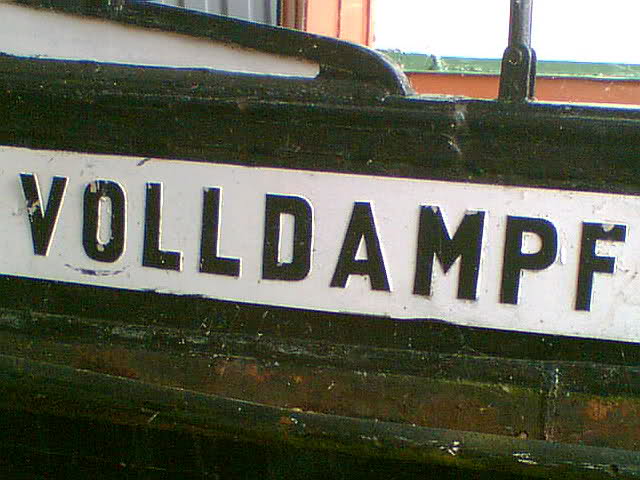
Namensschild historisches Dampfschiff
ich suche die schriftart dieses namensschildes aus stahl.
es handelt sich um das namenschild des schleppers "volldampf", baujahr 1896, des deutschen technikmuseums , siehe auch :
ich habe diese schriftart auch schon an anderen alten schiffen gesehen. ich glaube diese hier am dampfschiff "nordstern" müsste die gleiche sein, oder?
Wenn ich das richtig sehe sind das zwei verschiedene Schriften (das O sieht unterschiedlich aus). Ich glaube nicht wirklich dass es genau diese als Font gibt …
danke erstmal für die schnelle antwort! du hast wahrscheinlich recht damit, daß es sich um zwei unterschiedliche schriften handelt. bei näherem hinsehen (habe kein sehr geschultes auge..) fiel es mir auch auf.
markant finde ich die etwas gedrungene, schmale form der buchstaben, das "O", "D" und "P" wirken zudem fast eckig durch die kleinen kurvenradien der ecken.
ich habe schon ähnliche schriftarten gefunden, aber noch nichts zufriedenstellendes.
dein font passt schon sehr gut, besser als das was ich bisher hatte. die buchstaben sind allerdings noch etwas hoch, finde ich. und zu teuer für meine private vermutlich einmalige nutzung :oops:
… private vermutlich einmalige nutzung …
Was hast Du denn überhaupt vor? Die Zeile ist doch mit an Sicherheit grenzender Wahrscheinlichkeit ein Unikat und wird keine exakte Entsprechung in einer vorhandenen Satzschrift finden. Brauchst Du das für ein Modell? Dann ist vielleicht eine photographische Reproduktion bzw. ein Nachbau als Vector viel besser und schneller als die Suche nach einer ähnlichen Schrift.
Was hast Du denn überhaupt vor?
ich will ein reales namensschild (mit möglichst gleicher schriftart) für ein anderes schiff anfertigen. da ich andere/mehr buchstaben brauche, ist es mit einem vektornachbau der vorhandenen buchstaben leider nicht getan.
hm, Geld hat wie ich finde damit nichts zu tun. Ich denke wenn er hier ein wenig stöbert findet er auch was Schönes …
Okay, die beiden Vorschläge sind ähnlich, aber nicht wirklich okay, da das "M" in beiden Vorschlägen markant abweicht und der erste Vorschlag "zu schlank" ist. Nach meinen Recherchen kommt nachfolgendes Ergebnis am Ehesten an den verwendeten Font ran. Ich denken auch, dass der kreative Mensch, der das Schild gesetzt hat, sich nicht extra mit 2 Fonts - zumal dieser Schriftzug relativ simple daherkommt - auseinandergesetzt hat.
Eine etwas ausgefallenere Alternative wäre noch nachfolgender Font:
Hier sind die Rundungen z. B. interessanter.
Ohne ein bisschen Vectorfummelei wirds wohl nicht gehen, wenn es 1:1 sein soll aber ansonsten würde ich mich für die erstgenannte Version entscheiden.
das in dem beispiel ist doch bestimmt handgemachte typo (nach alten schablonen z. b.)
eine suche nach genau dieser schrift bleibt erfolglos, glaube ich.
die govan ist wiederum viel zu »rund«
... den runden (Gesamt) Eindruck der Govan erhält man aber nur durch das O und D, die übrigen Letter sind nahezu identisch... und um einen Ansatz zum aufwandsarmen Nachsatz zu haben, sicher eine gute (Font)Basis. Ich würde das Foto als Dateischablone nehmen und nachsetzen. Andere Schiffsnamen einfach dann davon ableiten und die fehlenden Buchstaben"schablonen" über Screenshots der Samples (Über Eingabe auf Fontseiten) nachbauen. Ist individuell, kostet keinen Cent nur Zeit... Sonnige Grüße
ich bin echt überwältigt! mit so reger beteiligung habe ich gar nicht gerechnet. da ich wie gesagt nicht wirklich vom Fach bin, waren die meisten beiträge sehr hilfreich, wie ich zu einer lösung kommen könnte.
so jetzt genug honig-um-den-bart, zu euren beiträgen:
@RobertMichael: die stahlbeton gefällt mir wirklich gut; inkl. "eckige rundungen" (sorry), und das "M" passt... danke für den Tipp, auch insgesamt gute site
@Persona.media: genau hingeschaut! deine vorschläge sind auch gut, bei der govan sind alle nichtrunden buchstaben super. die refrigerator ist innen zwar eckig und das "M" passt mal wieder nicht, aber das könnte ich relativ unaufwendig vektor-neubasteln bzw. etwas kombinieren. ich glaube auch nicht, das der hersteller zwei schriftarten verwendet hat.
Ich würde sogar so weit gehen zu behaupten dass das keine Schriftart, sondern wirklich ein Unikat ist :D
… ich hätte mir halt vorstellen können, daß auch dafür standards/ vorschriften existierten.
Es gab Verlage (wie Otto Maier Ravensburg), die Schriftmuster, z. B. für Schildermaler, herausgegeben haben. Aber das waren dann eher künstlerische Anregungen als Standards. Schon beim (natürlich händischen) anpassen an die Zielgröße dürfte es da zu Abweichungen gekommen sein.